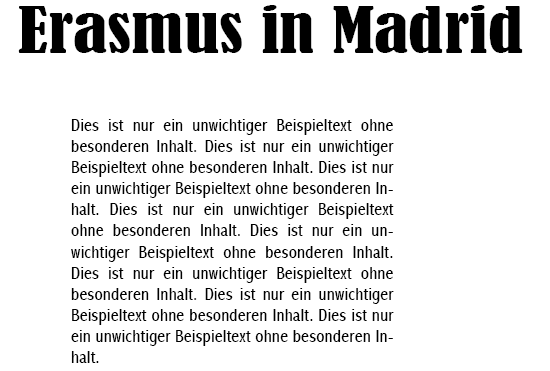
Kann ich diese beiden Schriften miteinander kombinieren
nach 7 Monaten Erasmus möchte ich nun so eine Art Bildband mit den besten Fotos und ein paar Texten erstellen. Da ich schon im Vorfeld die Bernard MT Condensed verwendet habe, soll die auf jedenfall auch im Bildband für Überschriften verwendet werden. Die Frage ist nur, welche Schrift für Texte am besten dazupasst. Ich finde ja die Abadi MT Condensed nicht schlecht.
Was meint ihr? Bin nicht so typografie-erfahren, aber ich finde, wenn vor allen Dingen die Bilder zur Geltung kommen sollen, dann macht sich eine Condensed-Schrift nicht schlecht, zumal die Überschriften ja auch in einer Condensed gesetzt werden. Irgendwelche anderen Vorschläge?
Nachtrag: Hmm.....im Screenshot sieht sie nicht so gut aus, wie im PDF-Dokument. Ist immer so eine Sache mit Screenshots und Speicherformaten :?
wie du schon angemerkt hast ist die Beurteilung anhand der Ansicht am Bildschirm schwierig um nicht zu sagen praktisch unmöglich. Ideal zur Beurteilung ist immer die Art in der produziert wird: Offset für Offset, Laserdrucker für Laserdrucker, etc.
Grundsätzlich habe ich anhand des Bildes den Eindruck, dass diese Schriften miteinander könnten – vor allem wenn der Größenkontrast so deutlich ausfällt. Die Abadi ist mir aber nur vom Hörensagen ein Begriff – nach einem kurzen Blick auf die Schrift bei Identifont kann ich zumindest sagen, dass ich diese Schrift nicht mag. Aber da spielen subjektive Vorlieben mit. Vielleicht hat ja einer der anderen Leser Erfahrungen mit dem Druckbild und kann etwas ›objektiveres‹ über die Zurichtung und die Satzbildqualität sagen.
Im Falle eines Bildbandes wird der Text wohl kurz ausfallen und somit wäre eine Condensed denkbar. Für längere Lesetextpassagen ist ein Schmalschnitt aber nicht die erste Wahl.
Ich würde sagen bezüglich der Formensprache passen sie zusammen, soweit ich das erkennen kann. Ob du ausgerechnet im Titel Serifen möchtest und im Lesetext nicht ist fraglich.
Das sehe ich nicht so. Das ist die übliche (dogmatische*) Sichtweise: Grotesk für Titel, Serifen für den Textkörper. Tendenziell ja, aber es ist nicht falsch das auch mal umzukehren (zumal die Bernard als Lesetype nun wirklich nicht geht).
Natürlich muss die Grotesk für den Lesetext eine gut lesbare sein. Aber je geringer die Textmenge, desto weiter kann man den Anspruch an die Lesbarkeit reduzieren und desto mehr hat man Freiraum für stilistische Kriterien (oder umgekehrt: ›Der Herr der Ringe‹ dann doch lieber in Bembo statt Helvetica ;-) )
danke für eure antworten. ich glaube nun, dass ich mit der Abadi MT Condensed nicht ganz falsch liege. Ich habe zunächst mit ein paar nicht-condensed-Schriften herumexperimentiert, aber zur Bernard, die ja auch condensed ist, passt irgendwie nur eine condensed für den Text. Da die Bilder im Vordergrund stehen, soll der Text kurz und unaufdringlich sein und vor allem neutral. Eine Serifen-Schrift hätte daher für meinen Geschmack schon wieder viel zu nobel ausgesehen. Schriften, die nur Anhängsel an Bildern sind, sollten am besten gar nichts aussagen.